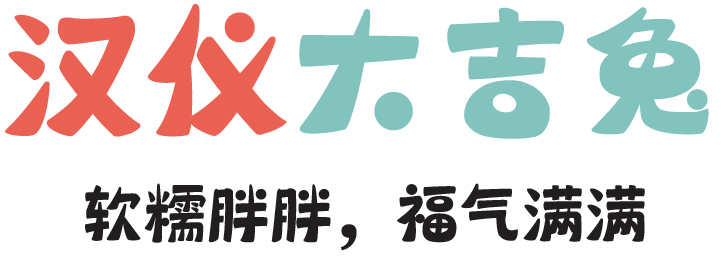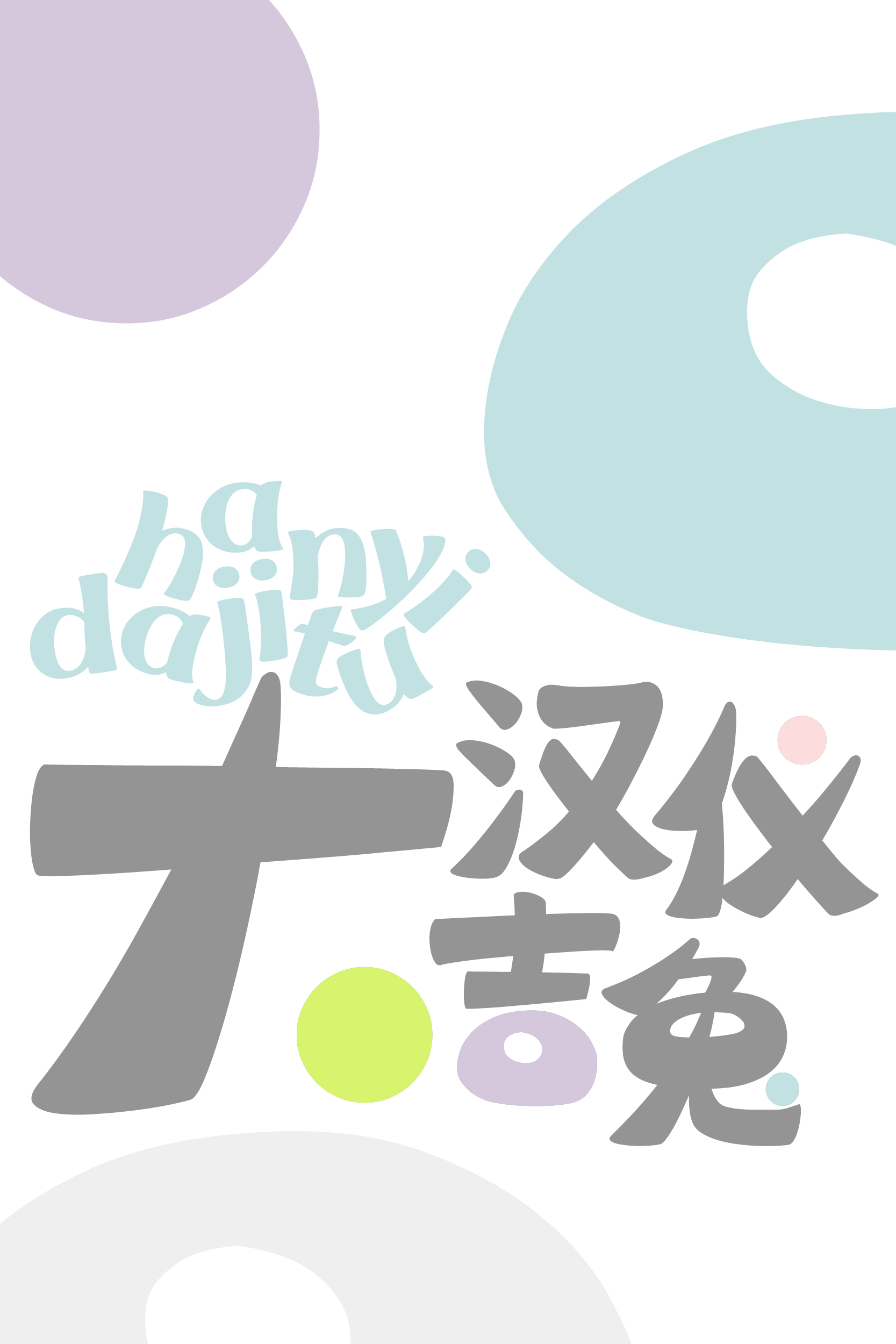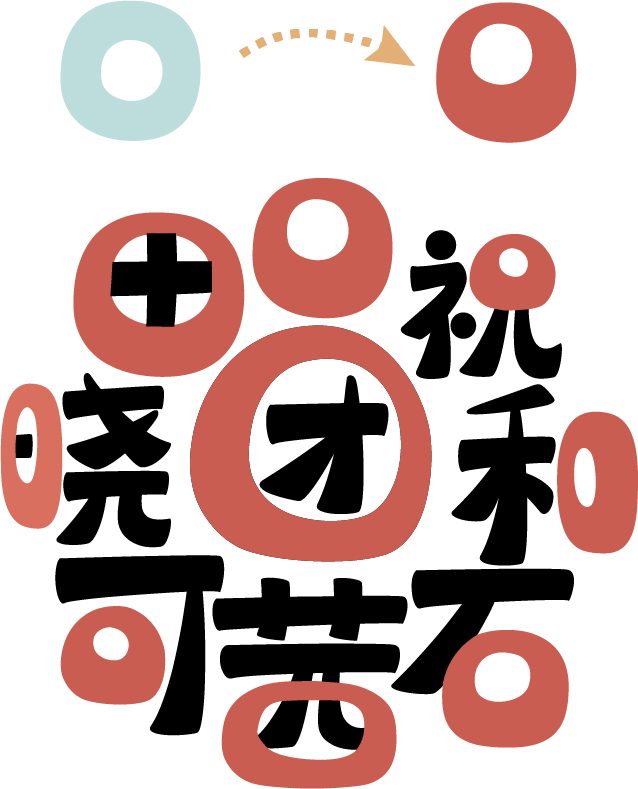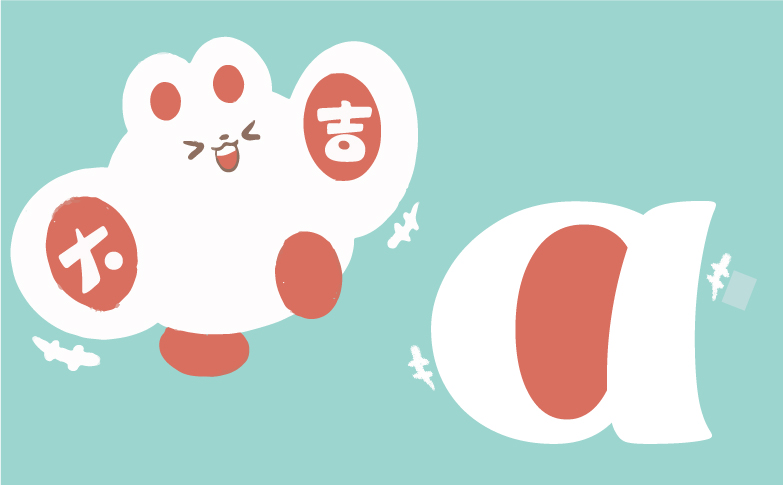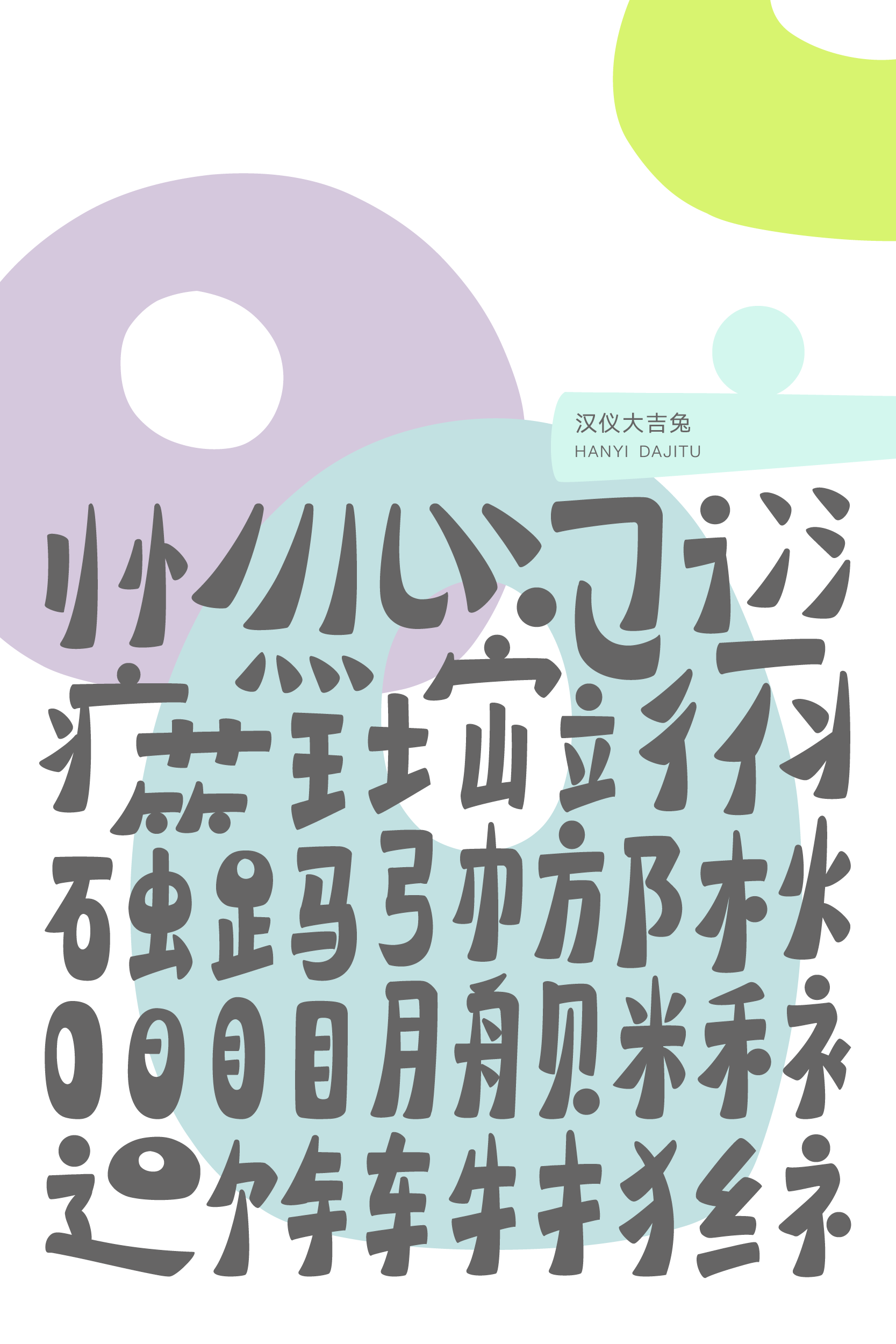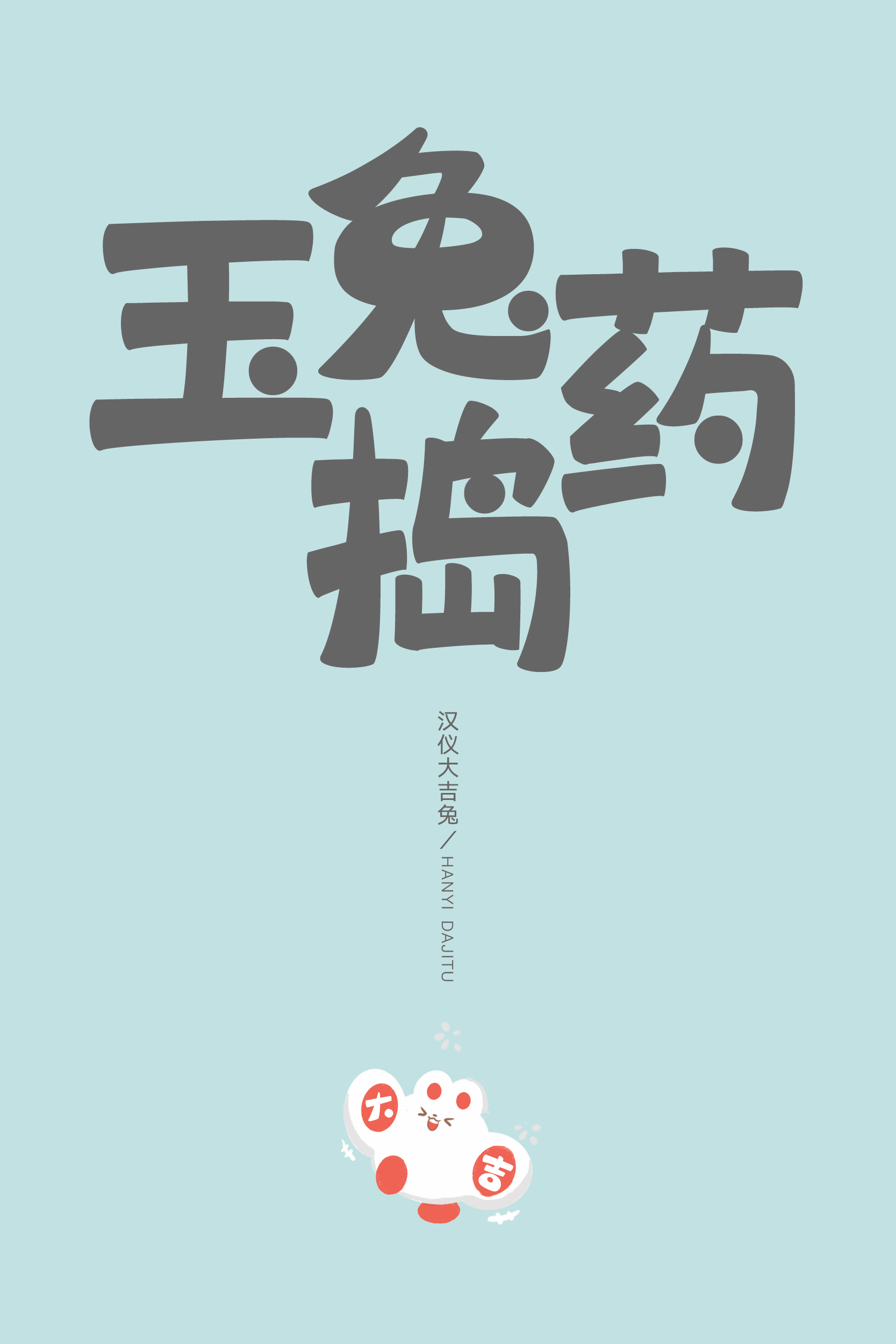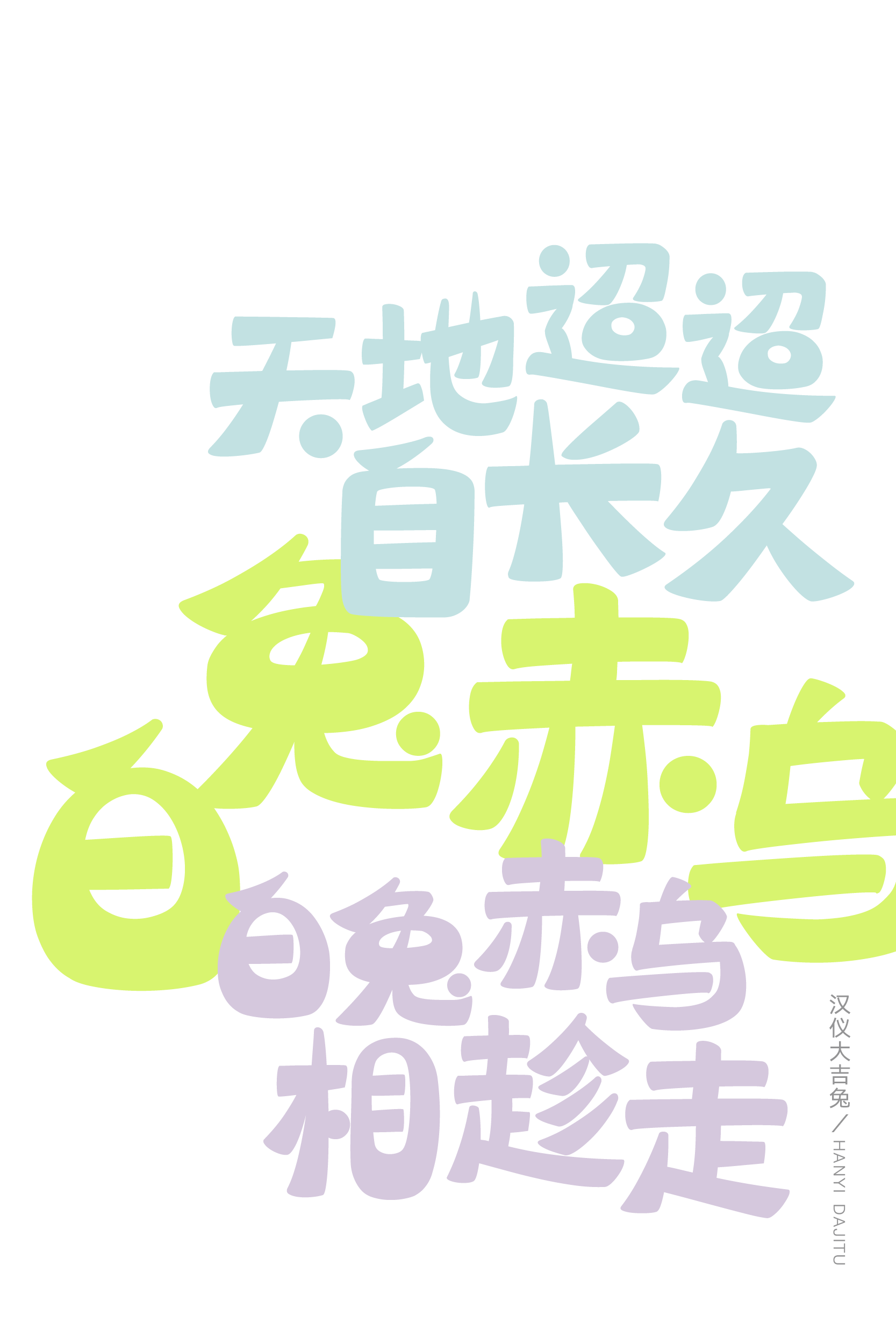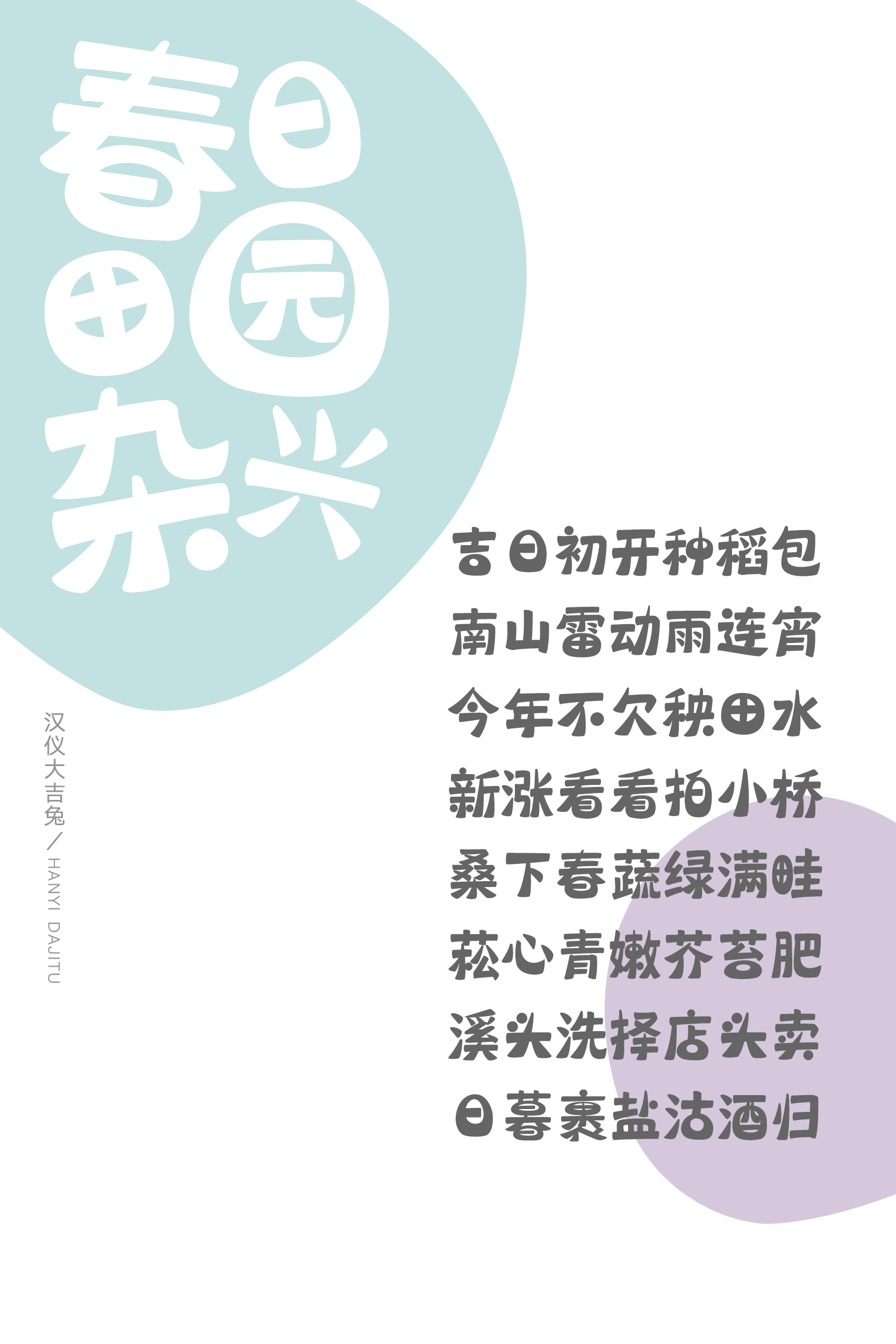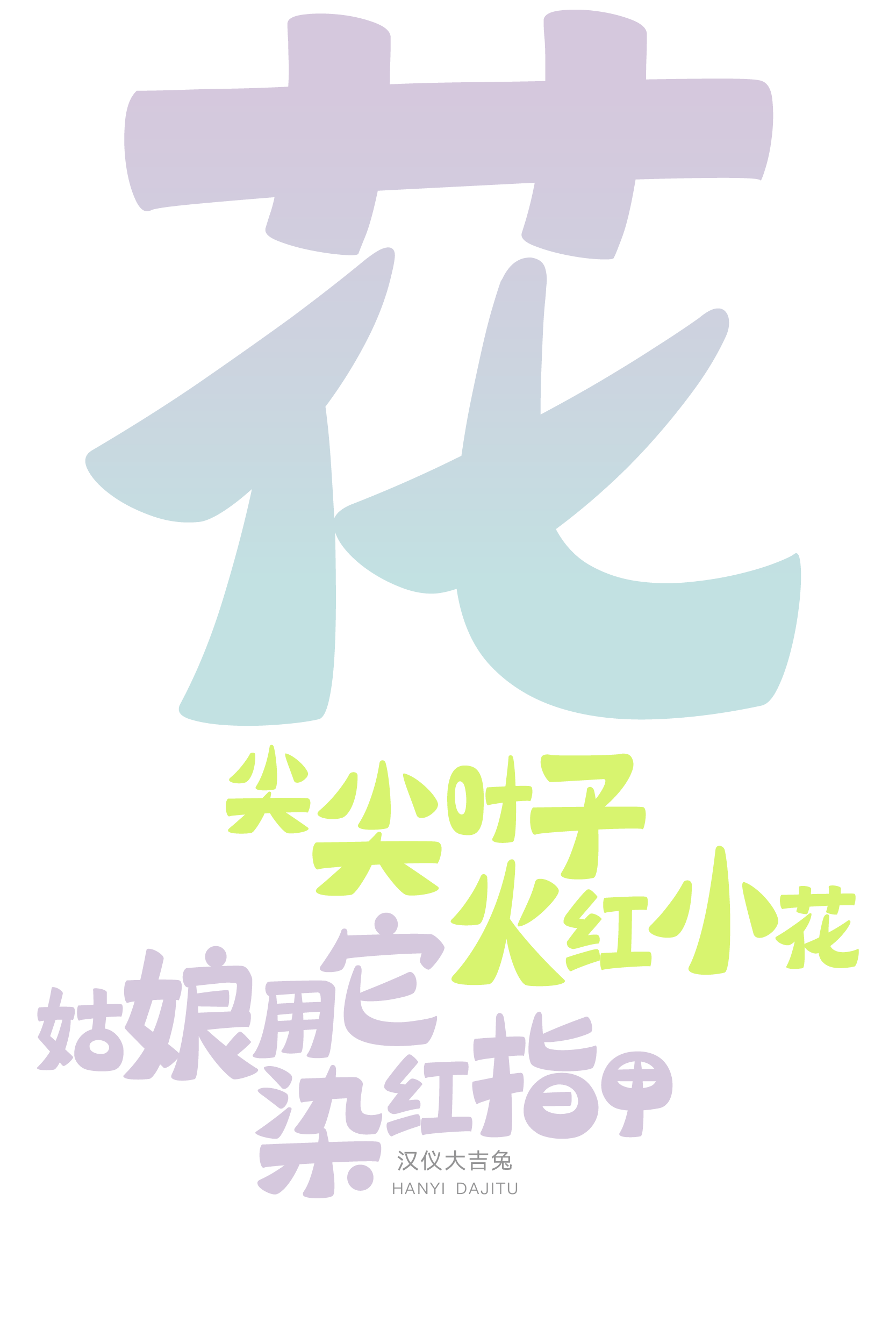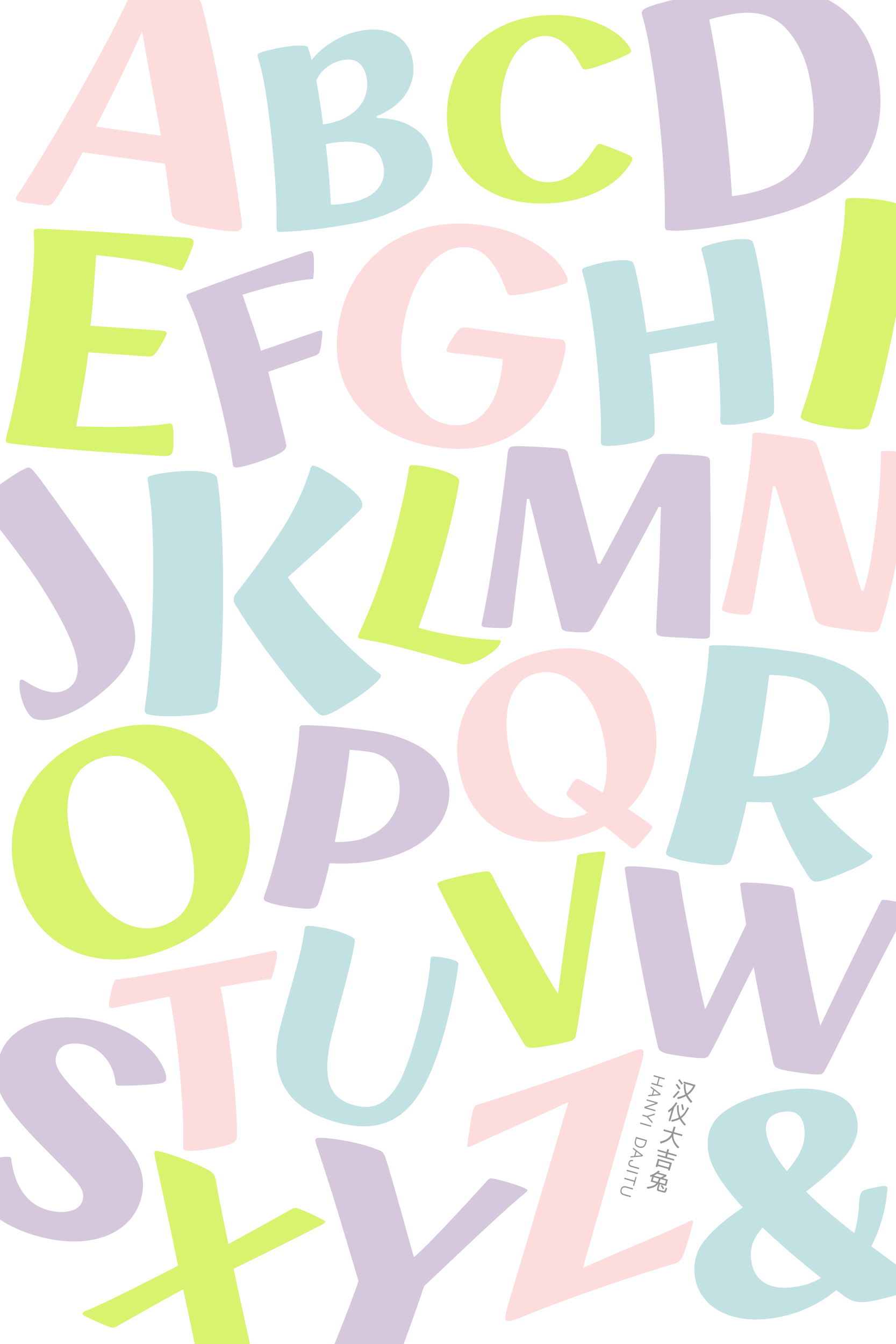
汉仪大吉兔字体介绍,一款有趣的创意字体
汉仪大吉兔是汉仪字库与大吉兔联合出品的一款创意字体。大吉兔是中式祈福文化的卡通形象IP,带有择吉祈福,助人心想事成的意蕴,旨在为大家带去健康,财富,爱情等好运。
汉仪大吉兔的设计灵感来源于大吉兔软萌的形象,融合了图形构成和微妙的手写感。这款字体轻松可爱,适用于logo、标题和短文案排版等场景。
汉仪大吉兔身材微胖,有着比较适中的字面和中宫,给人一种软萌萌的印象。字体重心稍稍向右倾斜,一副生动活泼的样子。
“口”部打破常规,做成了一个个圆圆的小团子。这些不对称的小团子像大吉兔胖乎乎的身姿,内白的位置随着部件位置改变而改变,笔画粗细对比俏皮可爱,成为吸引眼球的视觉焦点。
汉仪大吉兔圆圆的点像是兔子的小尾巴,从字体的不同角落冒出来,增添了几番趣味。笔画的出钩处被悄悄地藏了起来,使字形变得简洁且含蓄。
汉仪大吉兔竖画和撇捺上细下粗,一气呵成。笔画细节设计加入了马克笔手写的元素,干净利落。轻微的曲线弧度让字体变得更加亲切自然。
汉仪大吉兔的西文设计既参照了中文的笔形,也遵循了原文种的设计原则。独立的竖画不采用上细下粗的造型,而是运用微妙的弧度和粗细变化,活泼又不失稳重。转折处曲线流畅,粗细过渡自然。
小写a的造型采用了简洁大方的单层设计,和胖乎乎的大吉兔形象相呼应。